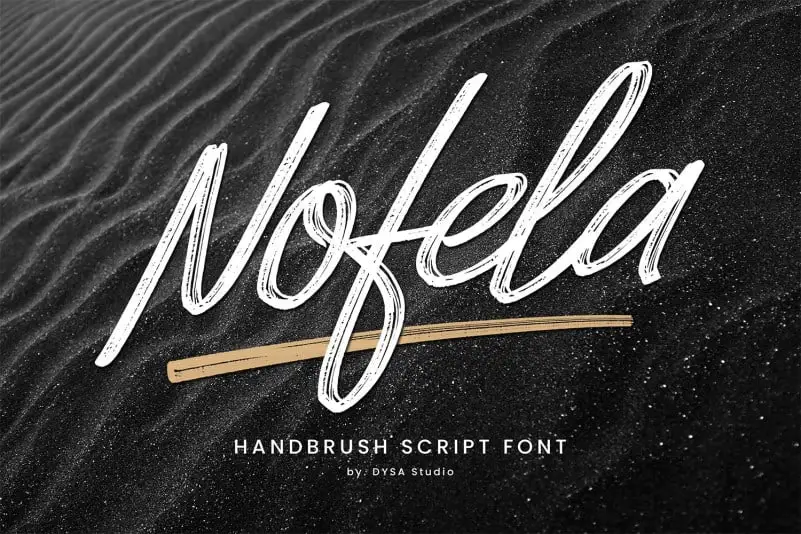
Nofela Brush Font – Download Grátis
A Nofela Brush Font é uma elegante tipografia criada para inspirar os projetos digitais mais criativos. Ela se move entre a arte manual e a tecnologia, com suas formas suaves e fluidas que parecem ter sido desenhadas por mãos humanas. Inspirada nos estilos de letra freestyle com pincel rápido, essa fonte é uma escolha perfeita para diversas necessidades, desde os projetos de marca até as mais sutis detalhes em fotos e vídeos. O design da Nofela Brush Font se destaca especialmente nas áreas como o branding de empresas, logomarcas, pacotes de produto ou mesmo a criação de arte digitais. Ela é perfeita para qualquer trabalho que exija um toque delicado e elegante. Seja para um projeto em social media, publicidade ou até mesmo para criar uma identidade visual personalizada com sua estética única. A Nofela Brush Font enriquece a textura de seus projetos digitais, tornando-os únicos e memoráveis, sejam eles invasões nas redes sociais, criação de arte digital ou até a composição de um site web. Com suas linhas suaves e seu design detalhado, a Nofela Brush Font traz uma atmosfera sofisticada e elegante ao design, tornando-a ideal para um leque amplo de aplicabilidades criativas. Seja em sua utilização como texto principal ou até mesmo como fundo ou marca d’água nas suas criações digitais, a Nofela Brush Font é uma fonte que irá encantar qualquer projeto visual que se destine a ser memorable e autêntico.